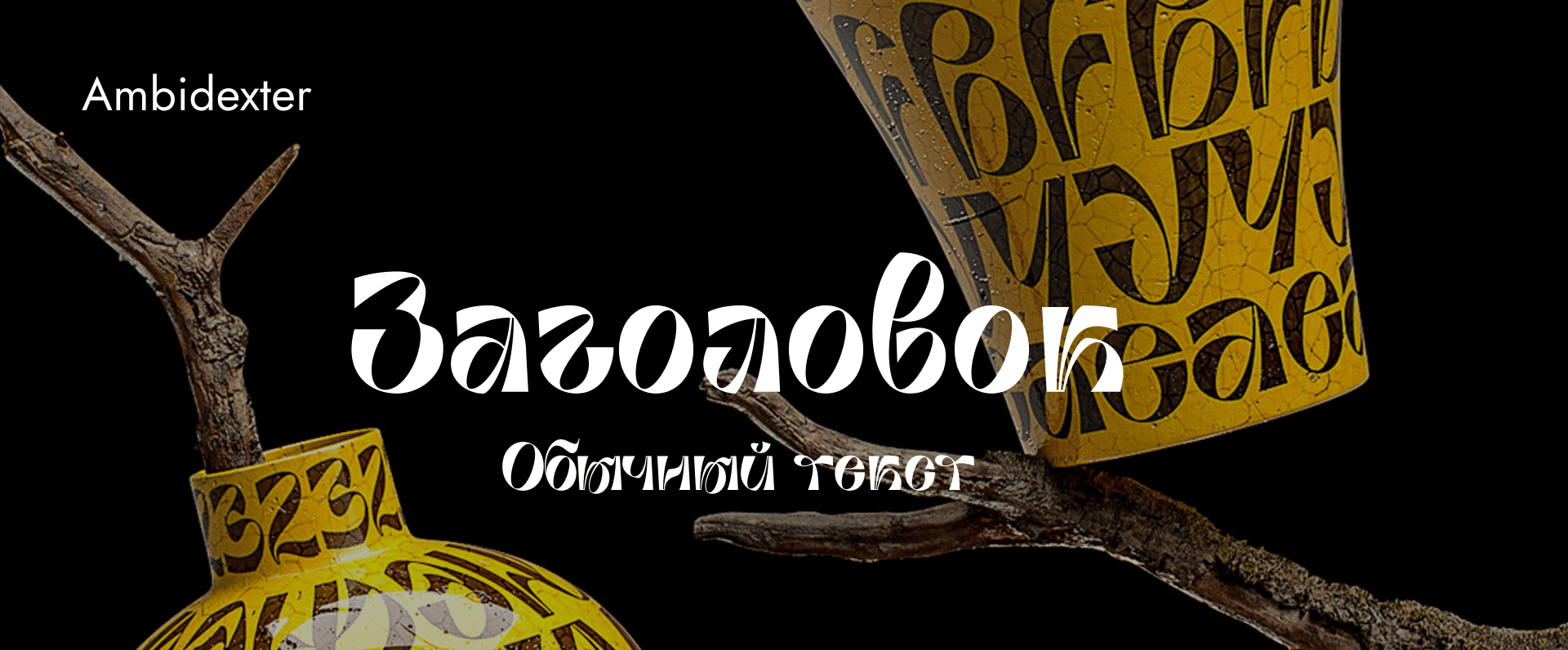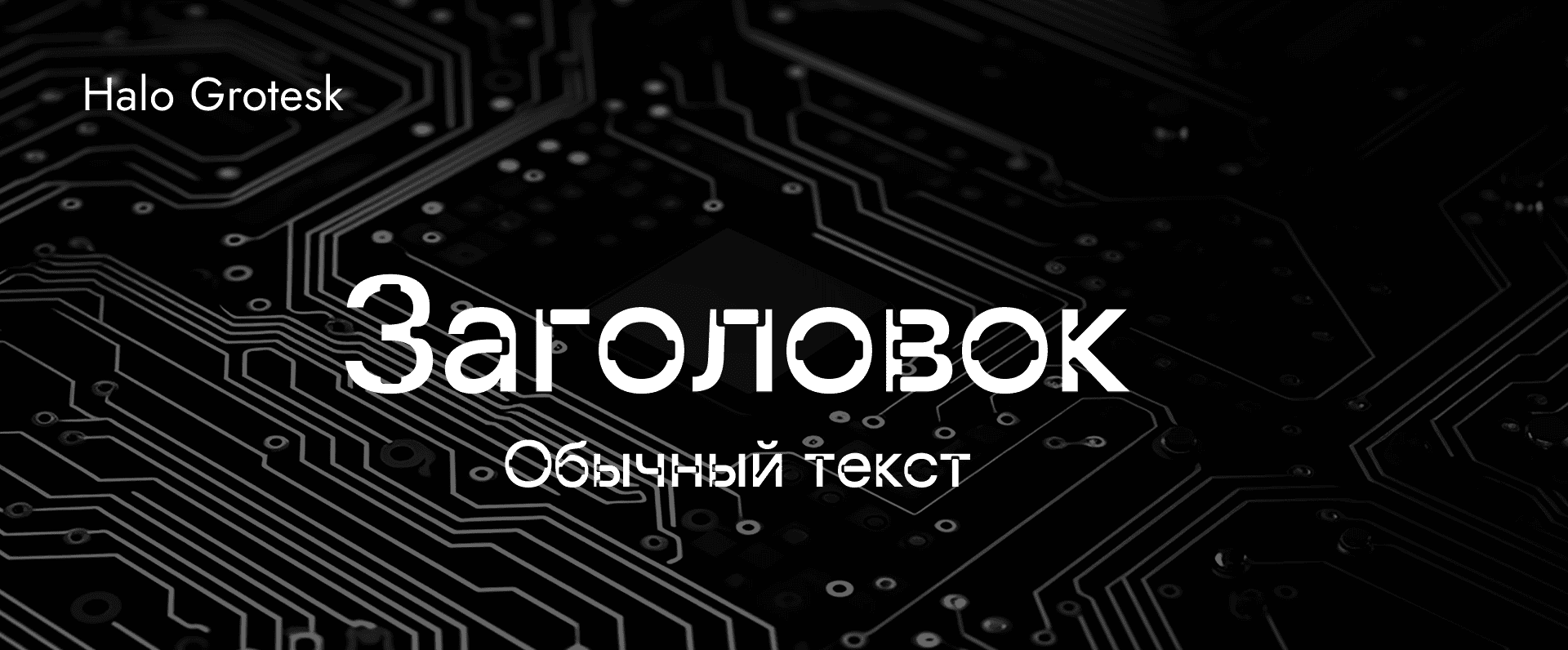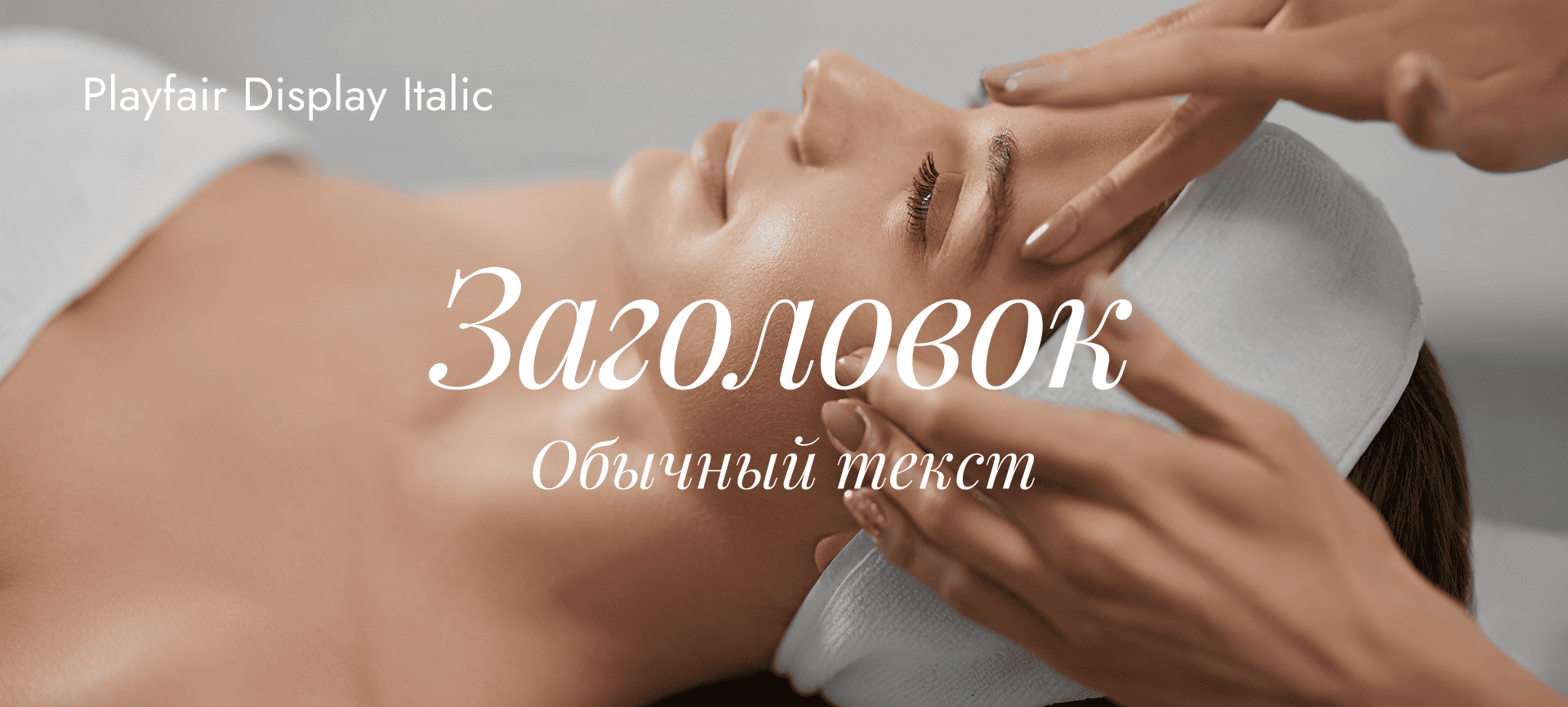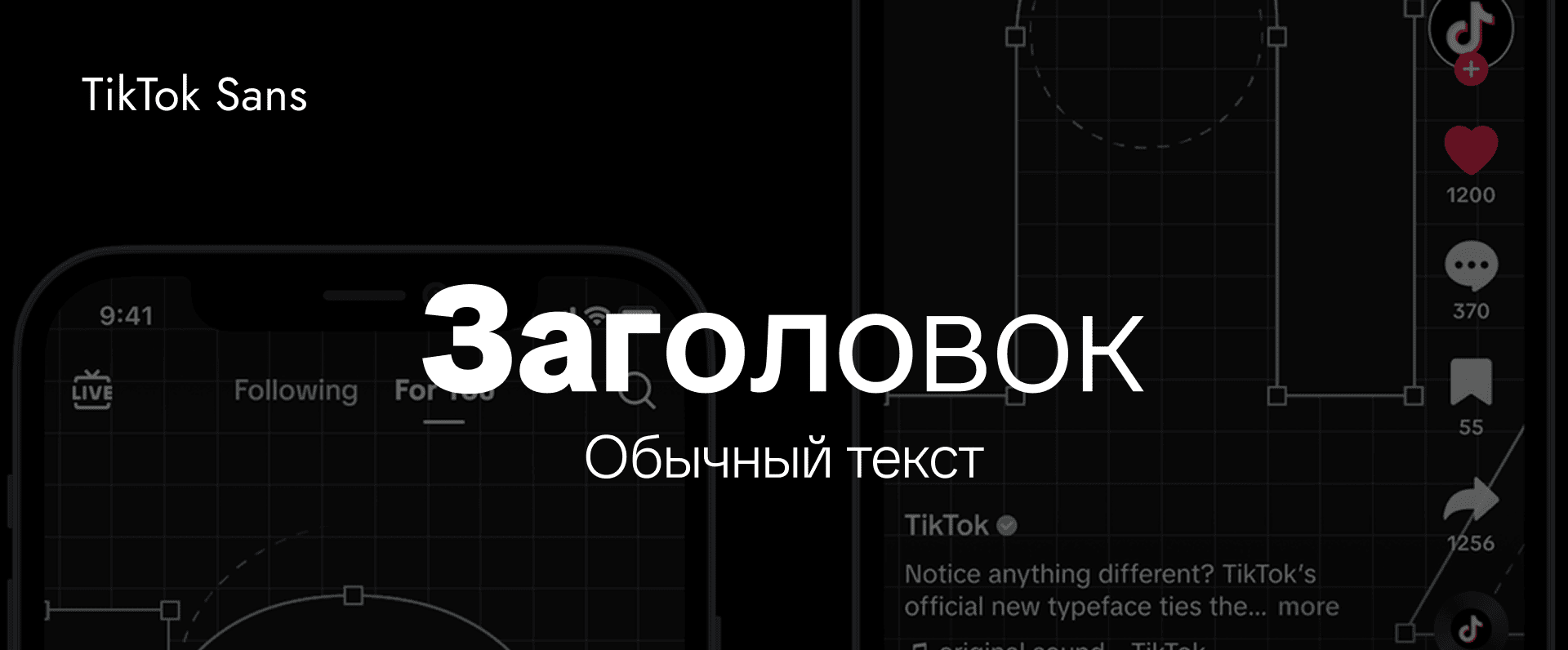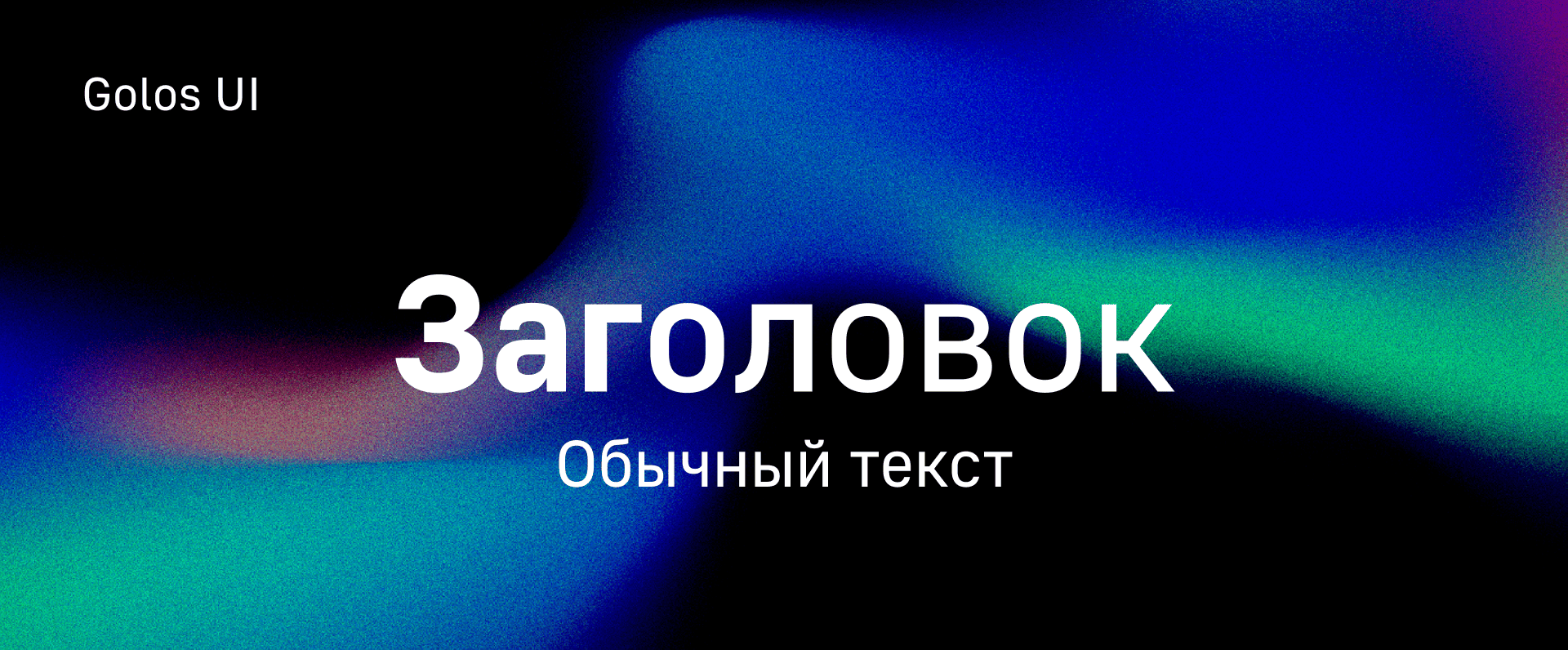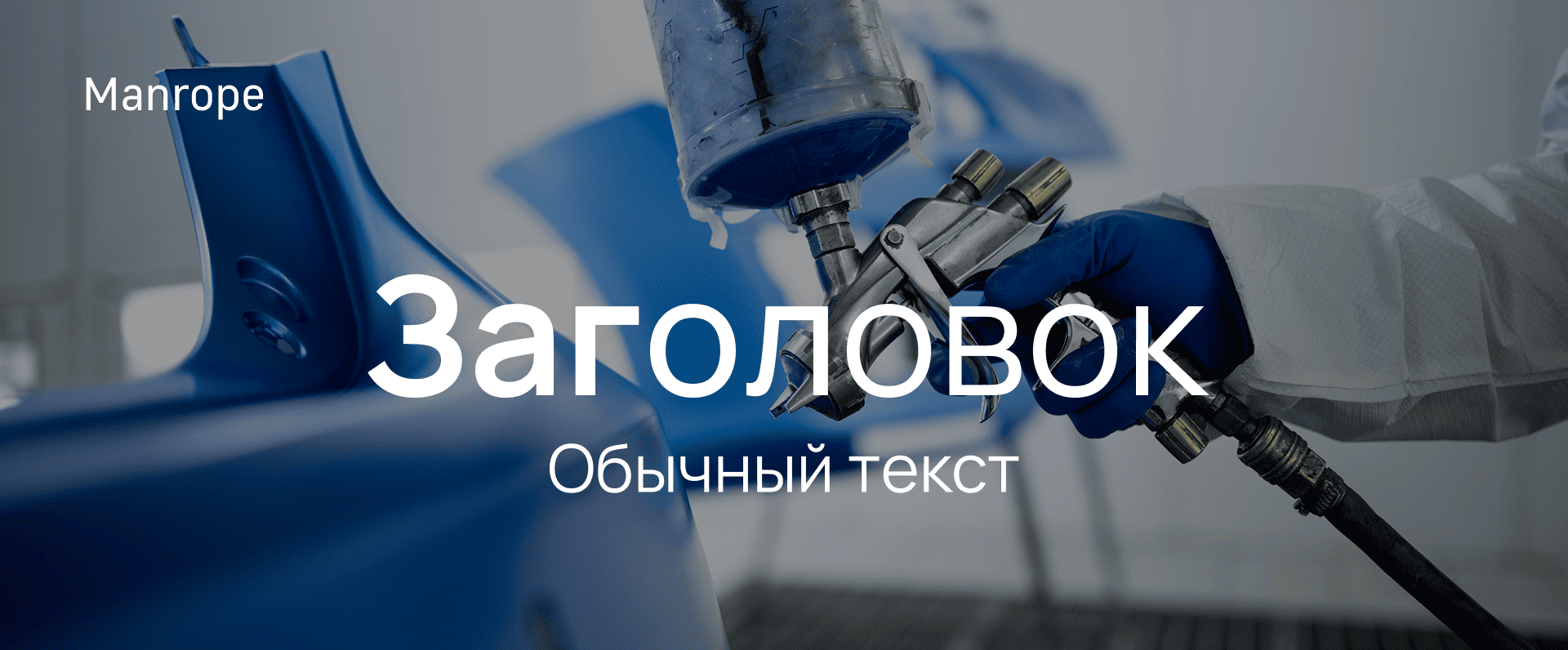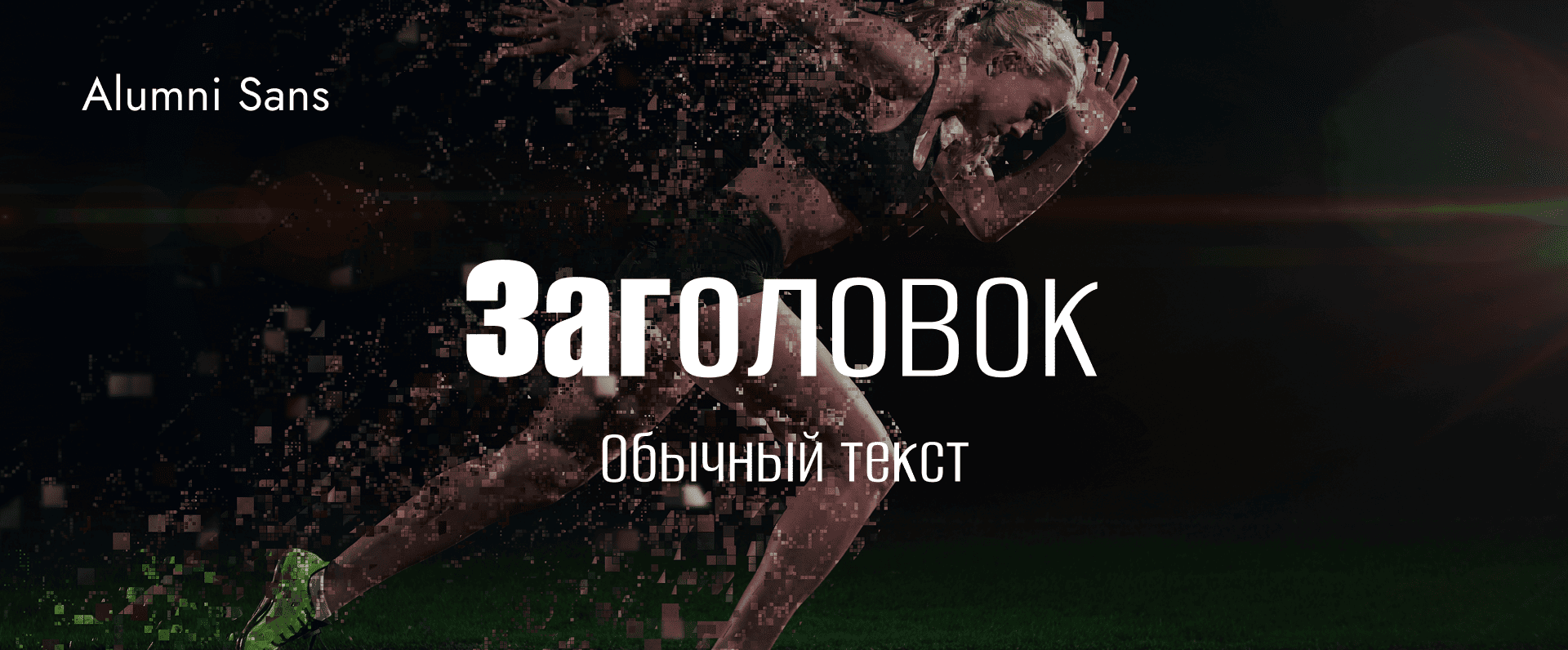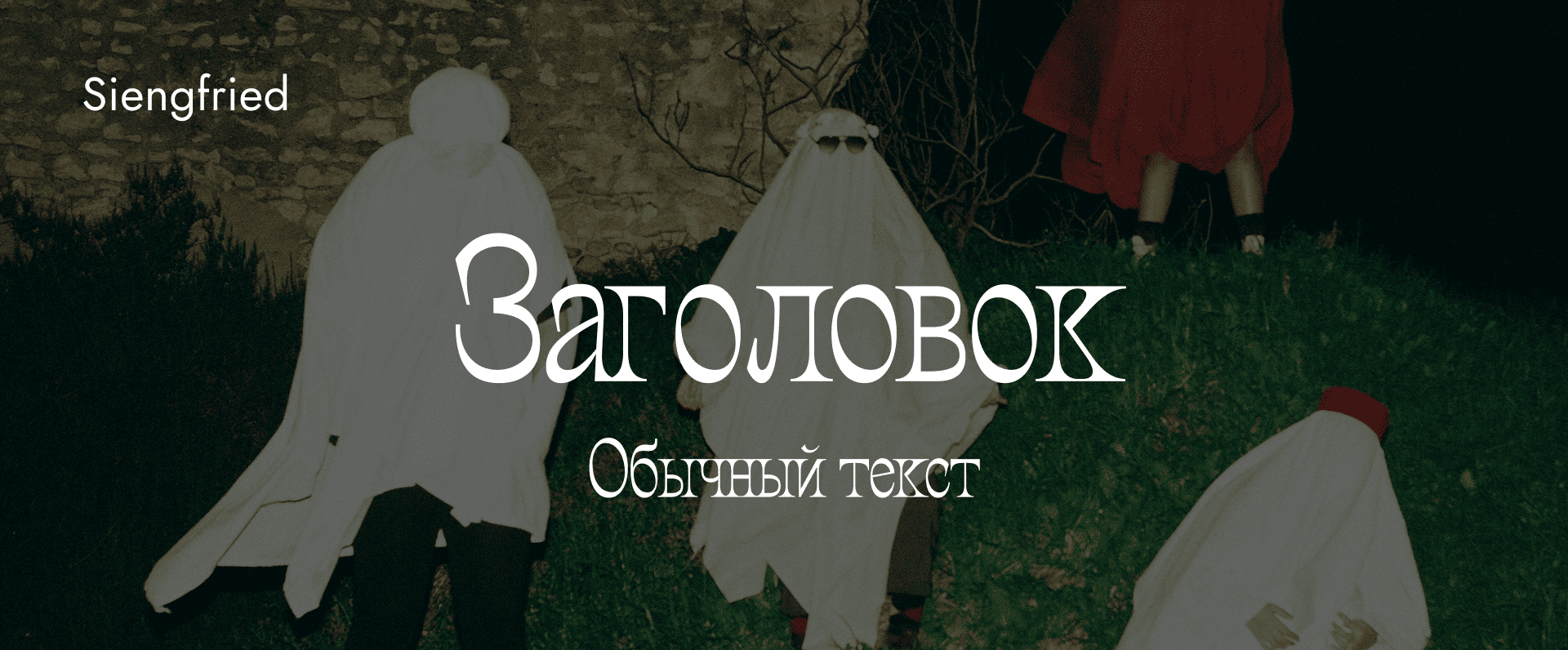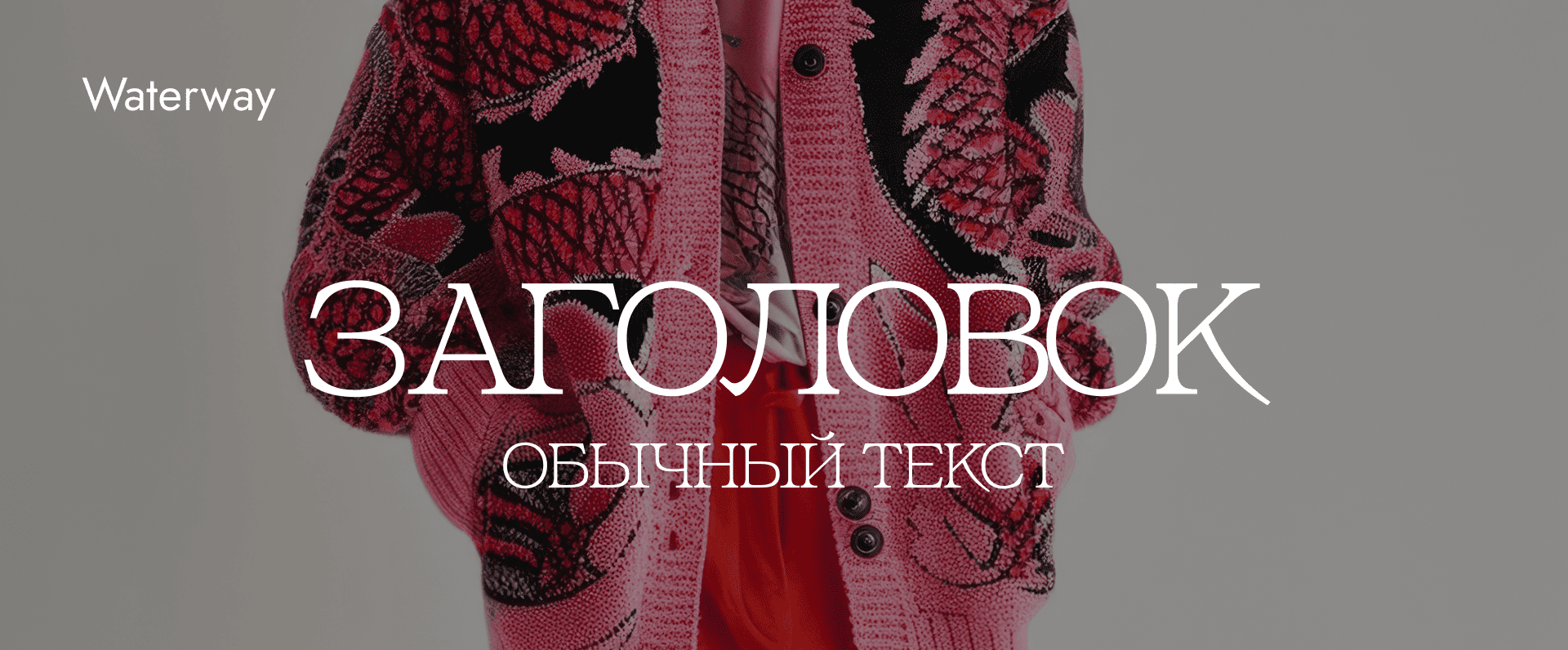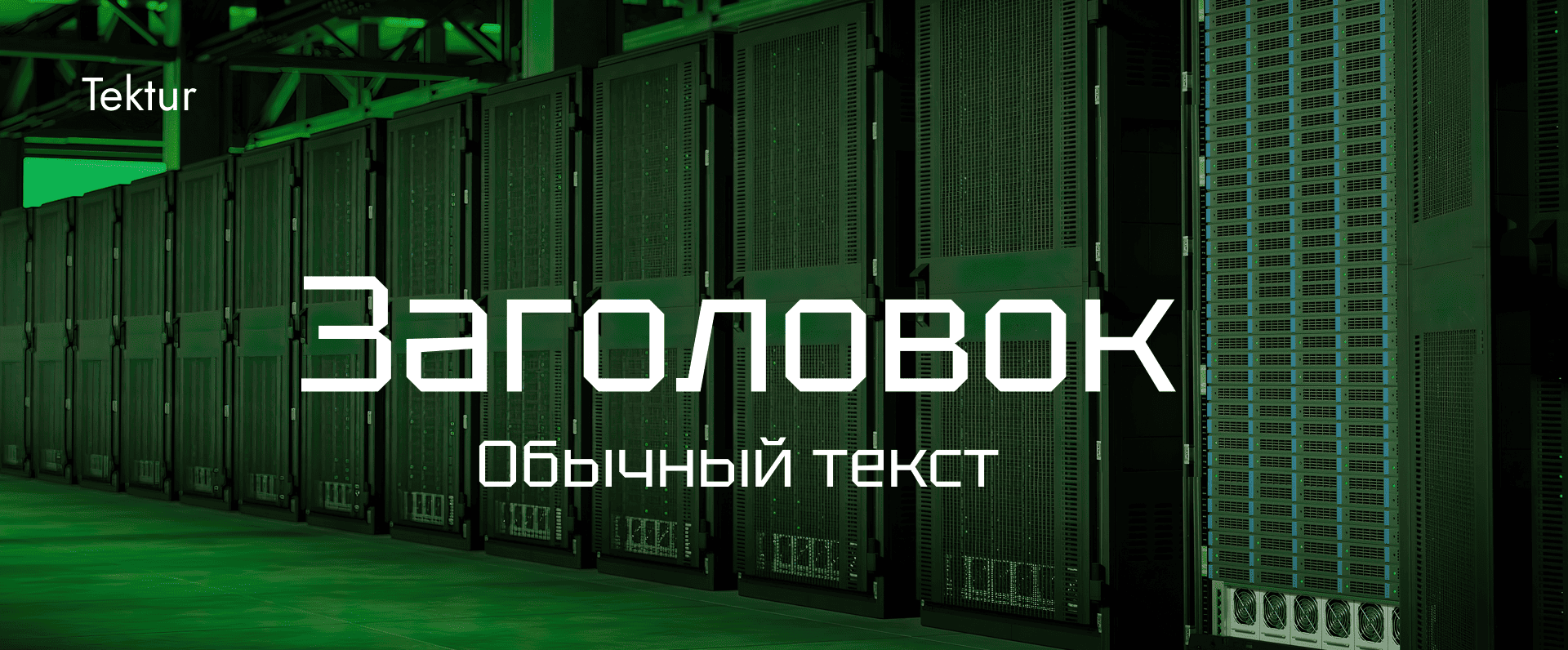
В 2026 году знак перестает быть главным героем, уступая место типографике. В условиях информационного шума брендам нужны более прямые и быстрые инструменты коммуникации — и шрифты справляются с этой задачей лучше любых абстрактных символов.
Рассмотрим ключевой элемент брендинга — шрифты. Буквы превращаются в чистый холст для передачи характера: они могут быть колючими или плавными, кричащими или строгими, но главное — они берут на себя роль визуального якоря бренда.
В этой статье разбираем главные тренды шрифтов 2026 года: возвращение выразительных засечек, тотальное доминирование крупных форм и чистую типографику в логотипах. А заодно показываем конкретные шрифты, которые уже задают этот новый сезон.
Рынок устал от «стерильности» гротесков, и современные антиквы дают бóльшую индивидуальность и живое ощущение. Они отлично адаптируются к цифровой среде.
Merriweather разрабатывался таким образом, чтобы сделать чтение с экрана максимально комфортным. В отличие от классических антикв с излишней декоративностью, шрифт выглядит современно, лаконично и устойчиво.
Oranienbaum — элегантный шрифт с легкими засечками. Хорошо подходит для текстов, где важен баланс между читаемостью и выразительностью. Отлично передаёт ощущение вдумчивости и серьезности, но без лишней строгости.
Playfair Display — элегантный шрифт, вдохновлённый эстетикой европейского Просвещения. Особенно популярен в дизайне проектов, связанных с модой, красотой и премиум-продуктами, где важна визуальная элегантность.
Waterway выглядит одновременно изящно и дерзко благодаря сочетанию тонких линий и острых засечек. Отличное решение, например, для косметических и модных брендов, которые хотят транслировать смелую элегантность.
Singfried — акцидентная антиква с колючим характером. Oсобенности шрифта — залипы, обратный контраст, засечки-шипы и выгнутые терминалы. Хороший шрифт для смелых, непростых проектов (магазин кастомной одежды).
Крупная типографика — ответ на информационный шум. Она привлекает внимание, задаёт ритм и создаёт иерархию. Тренд находит выражение в сверхкрупном кегле, смелых композициях, резких контрастах и асимметрии. Шрифт становится полноценным графическим элементом, а не просто носителем текста. Рассмотрим популярные варианты.
TikTok Sans — геометричный и чёткий гротеск. Его нейтральное, современное настроение идеально для цифровых интерфейсов, технологичных стартапов и молодёжной медиа-коммуникации.
Bounded. Экспериментальный вариативный шрифт с геометричными «обрезанными» формами. Его смелый, технологичный характер подходит для цифрового дизайна, креативных логотипов и акцентных заголовков в современных проектах.
Tilda Sans. Чистый и адаптивный гротеск, созданный для веба. Его нейтральное и дружелюбное настроение идеально для интерфейсов, корпоративных сайтов и диджитал-коммуникаций, где важны ясность и универсальность.
Uncage — строгий геометрический гротеск с лаконичными формами. Его сдержанное и современное настроение идеально подходит для технологичных брендов, интерфейсов и проектов в эстетике минимализма.
Mulish — современный гуманистический гротеск, мягкий и разборчивый. Его дружелюбная и открытая атмосфера отлично подходит для веб-чтения, образовательных платформ и брендов, ценящих доступность.
Golos UI - функциональный гротеск, созданный для интерфейсов. Его нейтральное и чёткое настроение делает шрифт идеальным для государственных проектов, корпоративных сервисов и приложений, где важна максимальная ясность.
Raleway - элегантный гротеск с удлинёнными элементами. Его лёгкое и современное настроение подходит для модных брендов, креативных студий и заголовков, где важны стиль и изящество.
Manrope — современный геометрический гротеск с открытыми формами. Его нейтральное и технологичное настроение делает шрифт универсальным, удобным для презентаций и дизайна IT-брендов.
Jura — геометричный гротеск с моноширинным характером. Его технократичное и чёткое настроение идеально подходит для интерфейсов и проектов в стиле киберпанк или sci-fi.
Geologica — вариативный гротеск с геометричной строгостью. Его современное и технологичное настроение идеально для цифровых продуктов, научных платформ и брендов, подчеркивающих точность и инновации.
Alumni Sans — гротеск с контрастными штрихами и спортивным характером. Его энергичное и динамичное настроение отлично подходит для молодежных брендов, спортивной экипировки и активного образа жизни.
Темп жизни сейчас слишком быстрый, поэтому люди редко внимательно вчитываются. Вместо этого они чаще сканируют информацию, останавливаясь только на заголовках. Крупная и акцидентная типографика, в свою очередь, помогает притянуть внимание к тексту. Несколько акцидентных шрифтов.
Postertoaster — жирный декоративный шрифт с плакатной эстетикой. Его дерзкое и энергичное настроение идеально для концертных афиш, уличного брендинга и креативных проектов, требующих яркого акцента.
В 2026 году типографика перестает быть просто способом донесения информации. Она становится самостоятельным инструментом брендинга — гибким, выразительным и запоминающимся.
Главное — выбирать шрифт осознанно, понимая, какой характер он транслирует. Ищите не универсальное решение, а то, которое будет говорить на одном языке с вашей аудиторией.